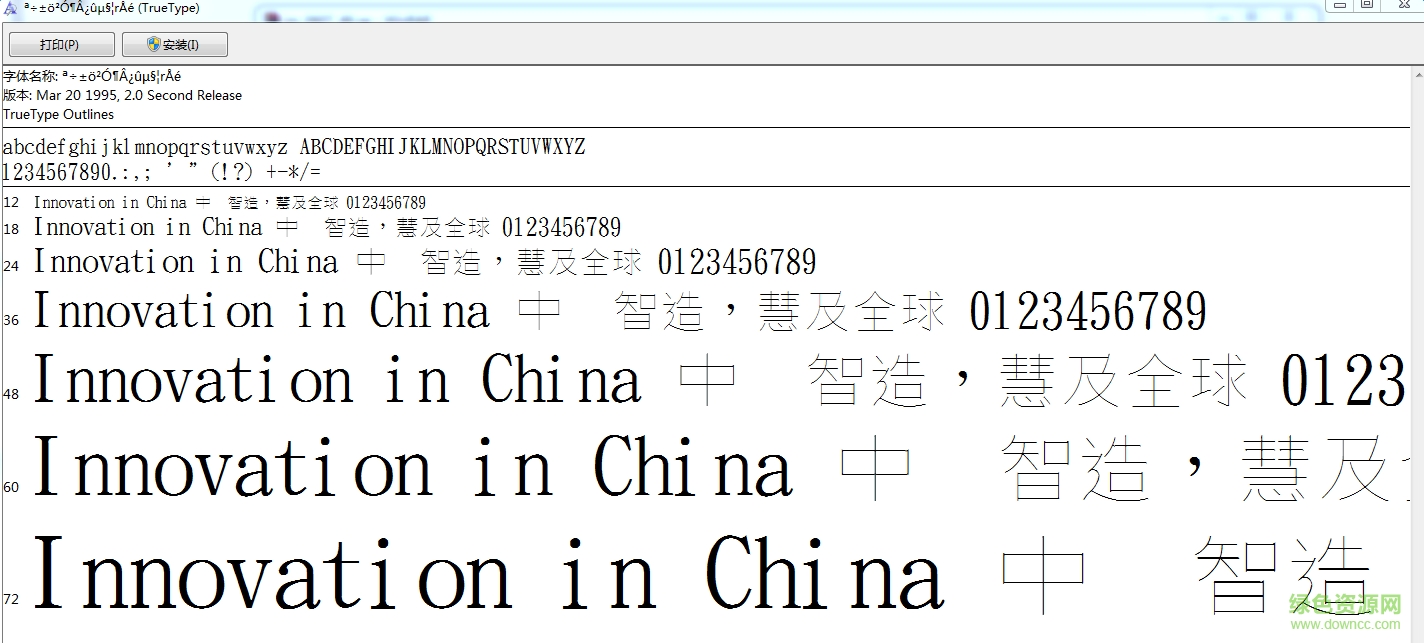
金梅細(xì)黑剛筆字體是一款金梅類細(xì)黑字體軟件,金梅類的字體給人非常正式的感覺,深受廣大年輕人和書法家的喜愛,還有更多好看字體盡情期待,歡迎到綠色資源網(wǎng)下載體驗!
金梅細(xì)黑剛筆字體是一款金梅類細(xì)黑字體,字體效果比較正規(guī),喜歡金梅類體字的朋友可以下載使用看看效果如何。